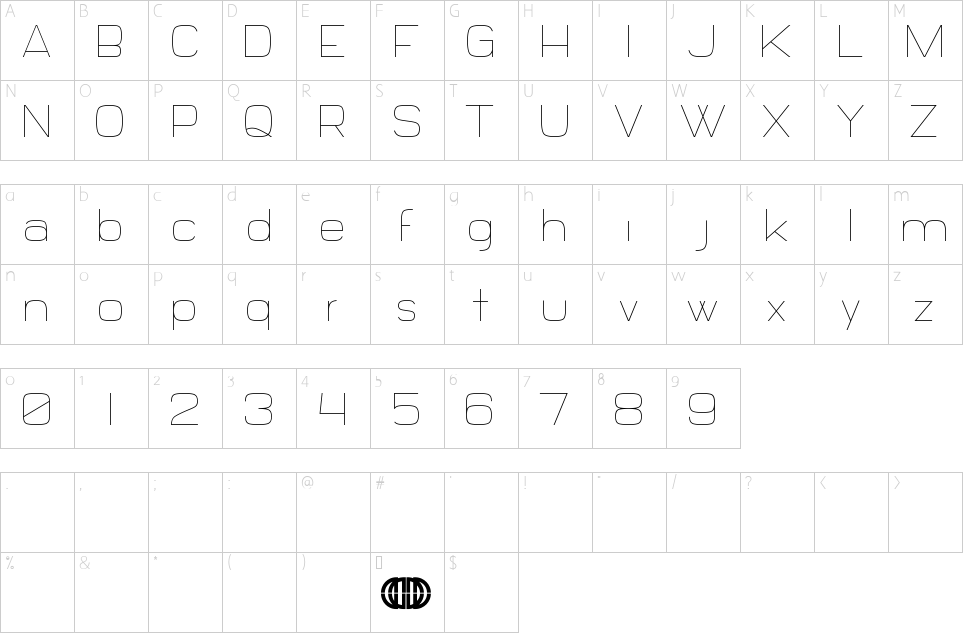
Descubra a elegância da Daiichi font aqui para Windows e Mac. Esta linheta foi desenvolvida por MuraKnockout Media & Design. Com seu design minimalista mas sofisticado, a Daiichi é perfeita para criar textos profissionais e impactantes. A fonte já foi baixada 10,051 vezes, demonstrando seu valor e popularidade entre designers de todo o mundo. Experimente agora e revolucione seu layout com uma mistura única de elegância e simplicidade da Daiichi.